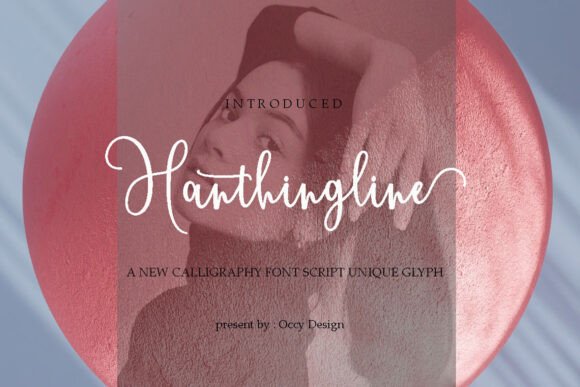
Hunthingline Script
適切なデザイン要素を見つけるのは難しい場合がありますが、Hunthingline Scriptは作品を即座に引き立てる優れたコレクションを提供します。
精密に作られたHunthingline Scriptは、クリーンなベクター、滑らかなタイポグラフィ、そして安心のための商用ライセンスを提供します。
POD(オンデマンド印刷)製品、結婚式の招待状、またはソーシャルメディアのグラフィックを作成している場合でも、Hunthingline Scriptは理想的です。